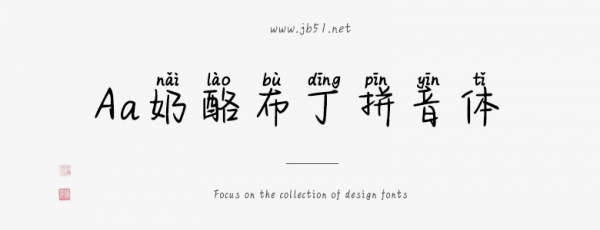
Aa奶酪布丁拼音體是一款不錯(cuò)的藝術(shù)字體,由Aa字庫(kù)出品,字體筆觸略細(xì),書寫流暢 ,具有很好的視覺感,適合應(yīng)用于藝術(shù)設(shè)計(jì)、平面宣傳設(shè)計(jì)、網(wǎng)頁設(shè)計(jì),書法字帖等領(lǐng)域,需要的朋友可以前來本站下載。